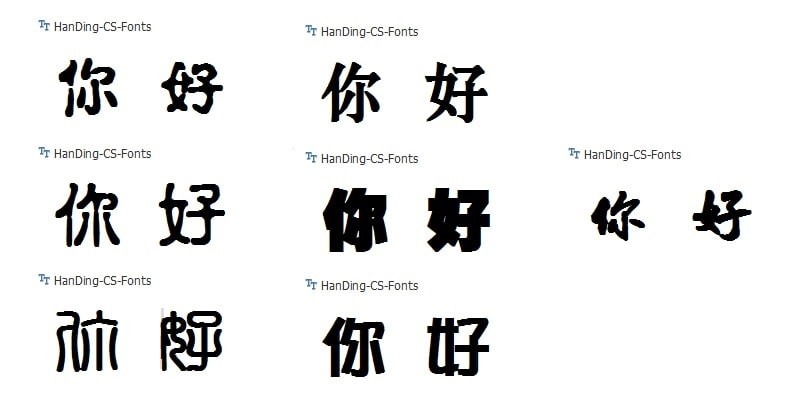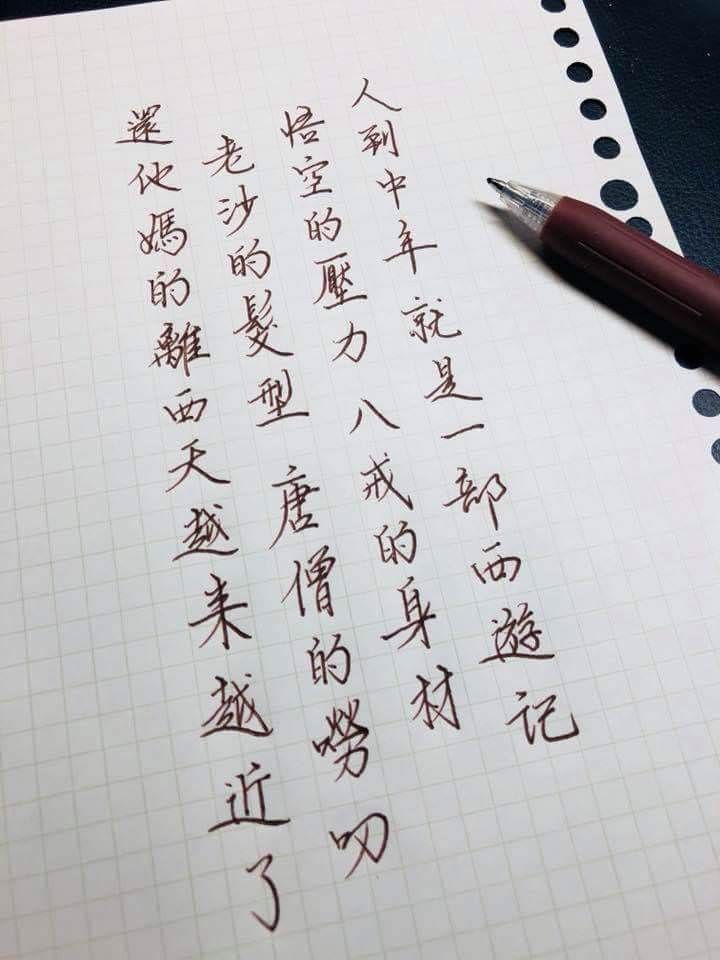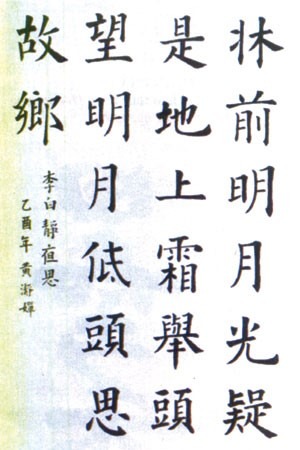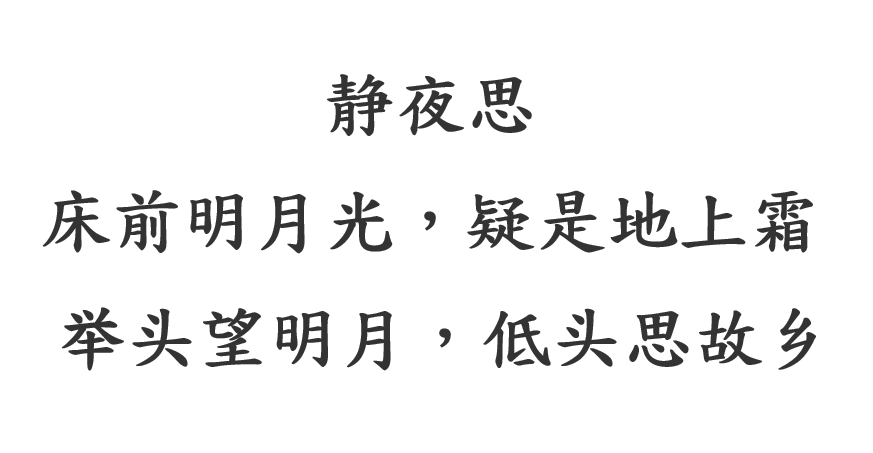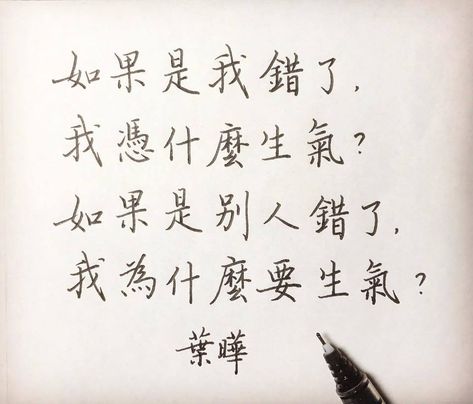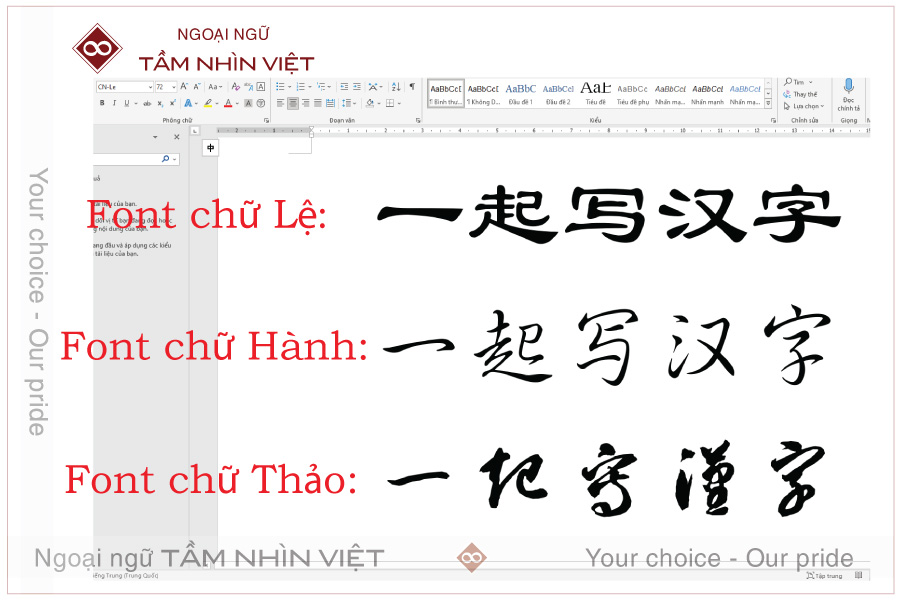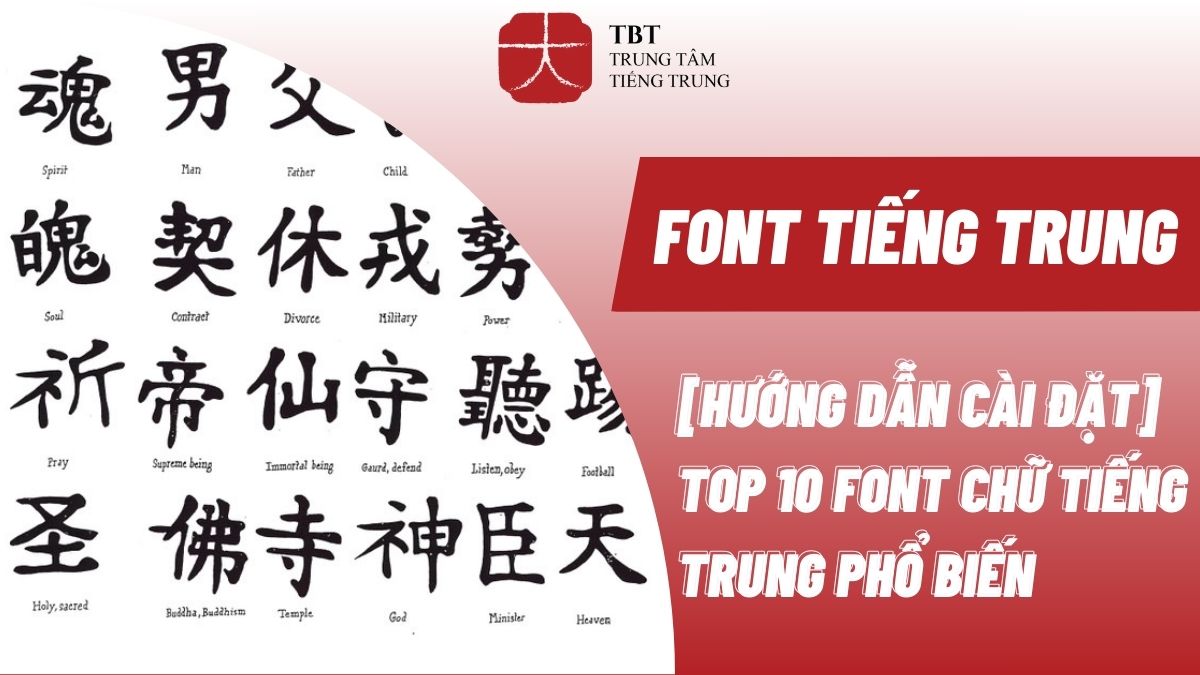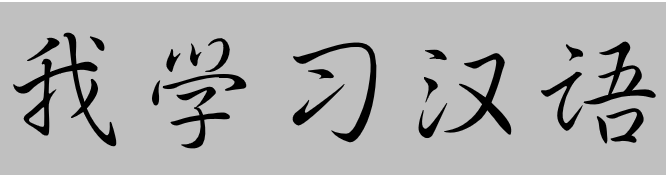
Font Chữ Hán Viết Tay
Việc sử dụng font chữ Hán viết tay ngày càng trở nên quan trọng trong lĩnh vực thiết kế, học tập và giảng dạy tiếng Trung. Những font chữ này giúp người dùng tái hiện nét đẹp truyền thống, sự mềm mại và tự nhiên của chữ viết tay, từ đó mang lại cảm giác gần gũi, sáng tạo cho mỗi văn bản. Bên cạnh các font chữ Hán viết tay đẹp, miễn phí, ngày nay còn có nhiều lựa chọn độc đáo, đơn giản hoặc truyền thống, phù hợp với nhiều mục đích khác nhau, dễ dàng tải về và sử dụng trên máy tính lẫn online. Bài viết này sẽ tổng hợp những font chữ Hán viết tay nổi bật, giúp bạn lựa chọn font phù hợp cho công việc của mình.
Font Chữ Hán Viết Tay
Font chữ Hán viết tay không chỉ mang vẻ đẹp nghệ thuật mà còn chứa đựng giá trị văn hóa sâu sắc. Trong số đó, các font như FZShuti hay FZYaoti đã thu hút sự chú ý của nhiều bạn trẻ nhờ vào những nét chữ mềm mại và dễ dàng sử dụng trong thiết kế. Bộ font này cũng bao gồm những kiểu chữ nổi bật như LiSu và YouYuan, tạo nên sự đặc sắc riêng cho mỗi tác phẩm.
Chữ Khải, một phong cách truyền thống, được viết bằng bút lông chấm mực tàu, vẫn còn được ưa chuộng ở nhiều nơi như Nhật Bản, Đài Loan và Hồng Kông. Chúng không chỉ đơn thuần là phương tiện để truyền tải thông điệp mà còn thể hiện nghệ thuật và tâm hồn của người viết.
Ngoài ra, việc sử dụng các font chữ viết tay như Cao Shu mang lại cảm giác tự do, phóng khoáng, rất phù hợp cho những ai yêu thích sự sáng tạo. Tổng hợp bộ font chữ tiếng Trung với những lựa chọn đa dạng này sẽ giúp bạn dễ dàng biến hóa tài liệu của mình thành những sản phẩm độc đáo, gây ấn tượng sâu sắc với người xem.
Font chữ thư pháp Hán độc đáo tay vẽ tinh xảo
Font Chữ Hán Viết Tay Đẹp
Font chữ Hán viết tay đẹp là một phần không thể thiếu trong thiết kế và nghệ thuật chữ viết. Trong số đó, font Simsun chính là một lựa chọn phổ biến nhờ vào sự ngay ngắn và dễ đọc. Được thiết kế không quá cách điệu, font Simsun thường được sử dụng để in sách cũng như tài liệu văn bản, mang lại sự trang trọng và tinh tế.
Ngoài Simsun, những font chữ như DFKAI-SB hay Chang Cheng giản thể cũng rất được ưa chuộng trong cộng đồng thiết kế. Đồng thời, font chữ KaiTi mang đến phong cách cổ điển, phù hợp cho những ai yêu thích sự lịch lãm. Đặc biệt, font Han Zi Việt Hóa rất lý tưởng cho các thiết kế cổ trang, như bìa sách hay typo, giúp gia tăng sức hấp dẫn cho sản phẩm cuối cùng.
Nét chữ Hán viết tay đẹp thanh thoát bay bổng
Font Chữ Hán Viết Tay Miễn Phí
Font chữ Hán viết tay miễn phí hiện đang trở thành một lựa chọn phổ biến cho những ai yêu thích thiết kế và sáng tạo. Với nét chữ mềm mại và dễ nhìn, chúng rất phù hợp cho việc in sách hay thiết kế phông bạt quảng cáo. Đặc biệt, Chill Font cung cấp nhiều kiểu chữ độc đáo, từ font không chân đến font viết tay, giúp mọi người dễ dàng tìm kiếm phong cách mình yêu thích.
Bộ sưu tập này không chỉ có trên 100 kiểu chữ khác nhau mà còn phong phú từ brush mạnh mẽ, handwritten tinh tế đến calligraphy mềm mại. Font Han Zi Việt Hóa mang đến nét đặc sắc cho các thiết kế cổ trang, giúp tạo nên những bìa sách hay cover ấn tượng.
Font chữ Hán viết tay tuyệt đẹp miễn phí
Font Chữ Hán Viết Tay Online
Noto Sans SC là một thiết kế không biến điệu dành riêng cho người sử dụng chữ Hán giản thể, hỗ trợ cả Hiragana. Bạn có thể tải xuống bộ font Trung Quốc Unicode, chọn và cài đặt các font chữ với định dạng .TTF để tạo ra những tác phẩm độc đáo, mang dấu ấn riêng của mình. Hãy khám phá và trải nghiệm sự sáng tạo với các font chữ này!
Mô phỏng chữ Hán viết tay trực tuyến độc đáo
Font Chữ Hán Viết Tay Đơn Giản
Font chữ Hán viết tay đơn giản là một trong những lựa chọn phổ biến và ưa chuộng trong lĩnh vực in ấn, đặc biệt là khi in sách hoặc quảng cáo. Nó không chỉ sở hữu nét đẹp thẩm mỹ mà còn rất dễ đọc. Với những đường nét mềm mại, font chữ này tạo cảm giác gần gũi và thân thiện, thu hút người nhìn ngay từ lần đầu tiên.
Tiểu triện, một trong những kiểu chữ Hán cổ điển, đã từng được sử dụng từ thời nhà Tần đến khoảng thời Tây Hán, nhưng sau đó đã dần được thay thế bởi Lệ thư với phong cách đơn giản hơn. Ngày nay, có rất nhiều font chữ tiếng Trung thông dụng như Simsun, DFKAI-SB, và KaiTi, giúp người dùng dễ dàng lựa chọn theo nhu cầu.
Font chữ Hán viết tay truyền thống tinh tế, nghệ thuật
Kết thúc bài viết, chúng ta có thể thấy rằng việc tìm hiểu và phát triển kỹ năng chữ Hán viết tay không chỉ giúp chúng ta nâng cao khả năng ngôn ngữ, mà còn mang đến một cái nhìn sâu sắc về văn hóa truyền thống. Chữ Hán không chỉ là một phương tiện giao tiếp, mà còn là một nghệ thuật thể hiện tâm tư, tình cảm. Hãy dành thời gian để luyện tập và cảm nhận vẻ đẹp của từng nét chữ. Qua đó, mỗi người sẽ không chỉ trở thành một người viết chữ Hán giỏi, mà còn là một phần của văn hóa và lịch sử lâu đời.